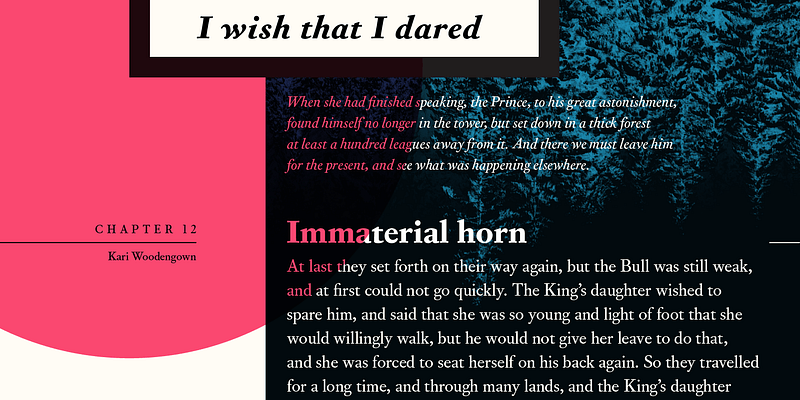
Basé sur les tailles moyennes de l’œuvre de Fournier, Corundum Text, avec ses majuscules généreuses et ses couleurs vives sur la page, est sans équivoque une police de texte de style néoclassique : lorsqu’elle est dépouillée de son vernis typographique, une brillance tranquille et nette émerge. Développant l’utilité des conceptions de Fournier pour la prose et la poésie, Corundum Text comprend deux graisses plus lourdes, chacune dotée d’un arsenal complet d’italiques et de petites majuscules, convenant à des textes subtils et immersifs ou à un affichage robuste avec une touche littéraire.